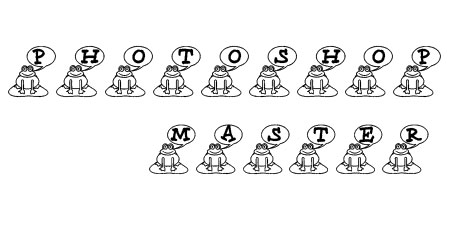
Дополнения Шрифты Татьяна Гапонова 26 июля 2009 Шрифт - Croakers JL Смешной шрифт с говорящими лягушками. Без поддержки русского языка Скачать Шрифт - Croakers JL